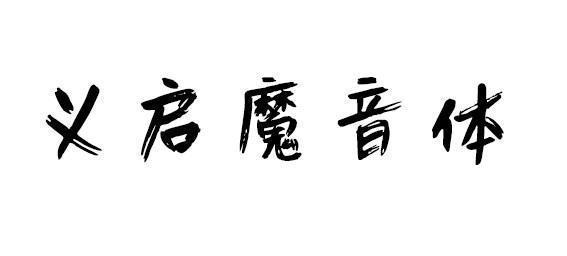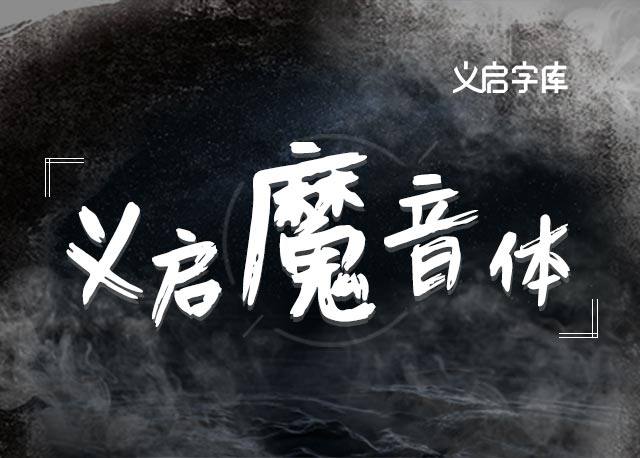
义启魔音体是一款非常有个性的创意书法字体,真的像魔音效果一样,分叉的实际效果,极致的表达了那类搞怪的响声,能够炸毁这个艳俗的世界。
这款字整体粗细适中,潇洒飘逸,极具个性,技法劲健而无失洒脱,动感而不失雄浑,临池不缀,涉足诸体。其整体字体效果出色。字体可以应用于海报展示、网页设计、影视制作、装潢设计、计算艺术设计、视觉设计、字帖等领域。